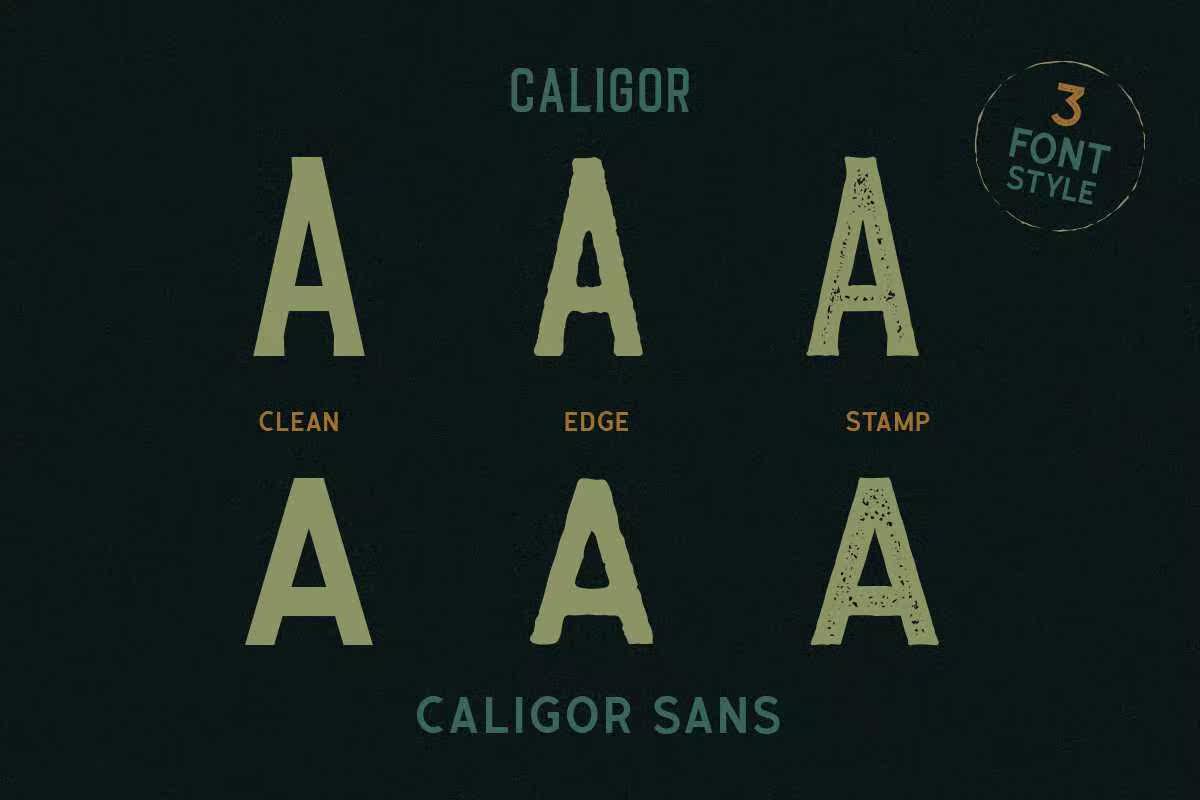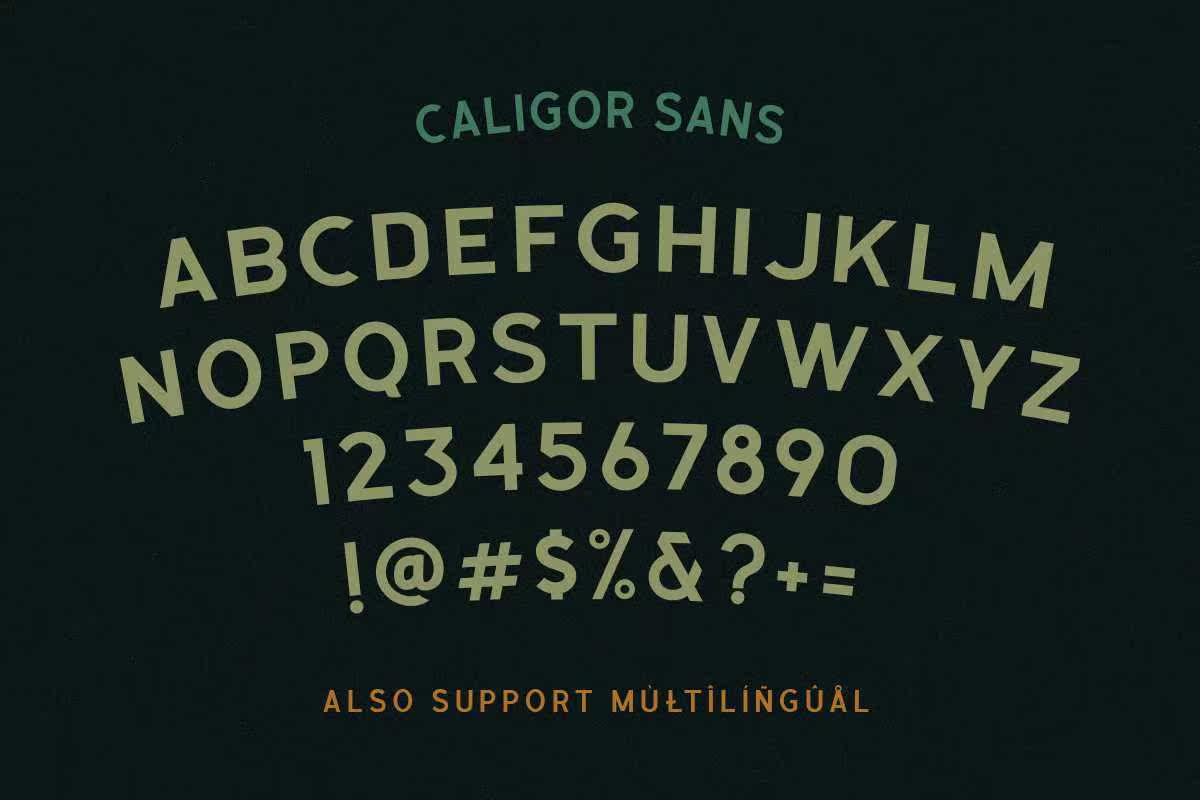
Caligor是一个显示字体系列,适用于标题、标识、服装、邀请、品牌、包装、广告等需要字体的用户。此字体包括大写、小写、标点符号、符号和数字、样式设置、替换、连字、,EtcalSo支持多语言和ReadyPuaEncoded。Caligor是一个显示字体系列,适用于需要标题、标识、服装、邀请、品牌、包装、广告等字体的用户。此字体包括大写、小写、标点符号、符号和数字、文体设置替换、连字等。EtcalSo支持多语言和ReadyPuaEncoded。